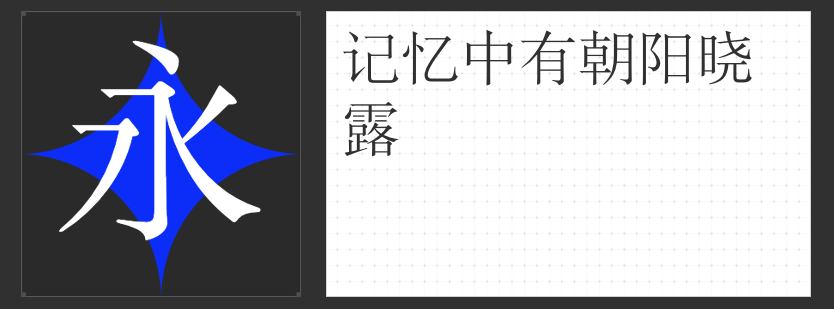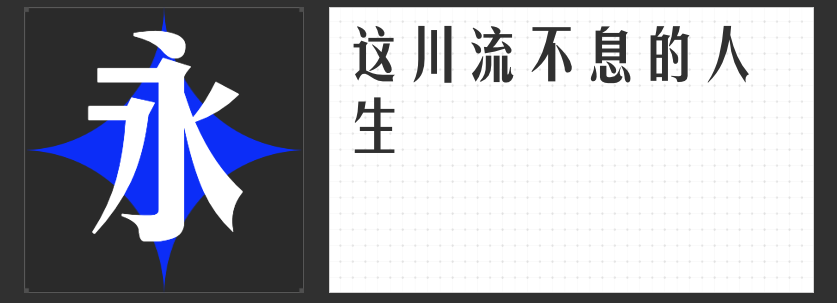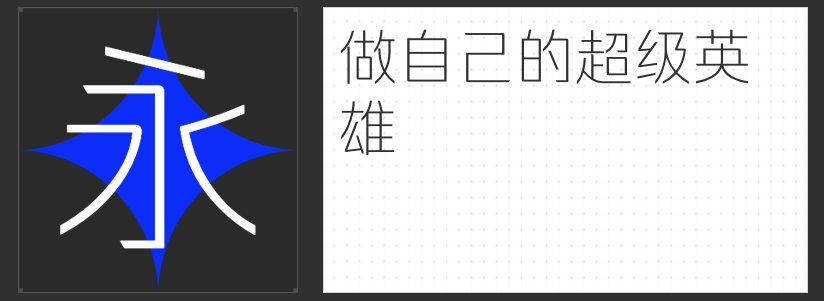
职场设计全能搭子!四款高适配内嵌字体深度解析
在PPT演示、品牌提案或数字出版物设计中,内嵌字体的稳定性直接影响最终呈现效果。本次精选四款「励字」系列字体,均以嵌入式场景为核心优化,兼顾美学表达与功能需求,堪称多场景设计的效率工具。
一、励字美黑简
融合黑体骨架与宋体韵致的「励字美黑简」,以黄金比例平衡笔画粗细。其横竖笔画的微妙粗细差,既保留黑体的力量感,又融入宋体的书卷气,尤其适合年度报告、商务PPT等正式场景。嵌入文档后,标题文字在投影幕布上依然保持锐利的视觉焦点,副标题则自带书香气质,完美平衡专业性与可读性。
二、励字超级勇士简 特细
这款特细字重黑体通过收窄中宫、延长笔画末端,创造出科技产品的冷峻感。0.8mm的极细笔锋在嵌入高分辨率屏幕后,仍能清晰展现几何切割的棱角,非常适合数字产品界面、科技峰会海报等场景。其超窄字距设计还支持多语言混排,英文标题与中文正文切换时保持视觉统一性。
三、励字书宋简繁
复刻清代雕版宋体的「励字书宋简繁」,将横轻竖重的古典法则转化为现代屏幕适配版本。嵌入印刷级PDF后,小字号正文仍保持开放式的中宫呼吸感,连续阅读不易疲劳。特别适合法律合同、学术论文等需兼顾权威感与易读性的场景,繁体字符库更支持两岸三地商务文档流通。
四、励字仿宋简繁
从宋刻本中提取基因的「励字仿宋简繁」,将楷书的起收笔弧度与宋体的结构框架融合。嵌入电子书后,其均匀笔粗在灰阶屏幕上呈现木质印刷品的温润质感,适合古籍研究专著、文创产品设计说明等场景。简体与繁体版本均采用中性字重,确保跨版本内容更新时的视觉连贯性。
四款字体均通过OpenType特性优化,嵌入Office、Canva等工具后无渲染损耗。从商务汇报到文化传承,从数字界面到印刷品,这些「隐形的设计助手」正以工业级稳定性,重新定义职场设计的效率边界。